Декоративные шрифты для вашего дизайна
Пополняем коллекцию шрифтов. Сегодня мы собрали свежие и бесплатные примеры декоративных шрифтов. Оно подойдут для больших надписей, чтобы подчеркнуть то или иное настроение ваших дизайн-проектов. Используйте их для заголовков, оформления лозунгов или поздравлений на открытках.
Romero Regular
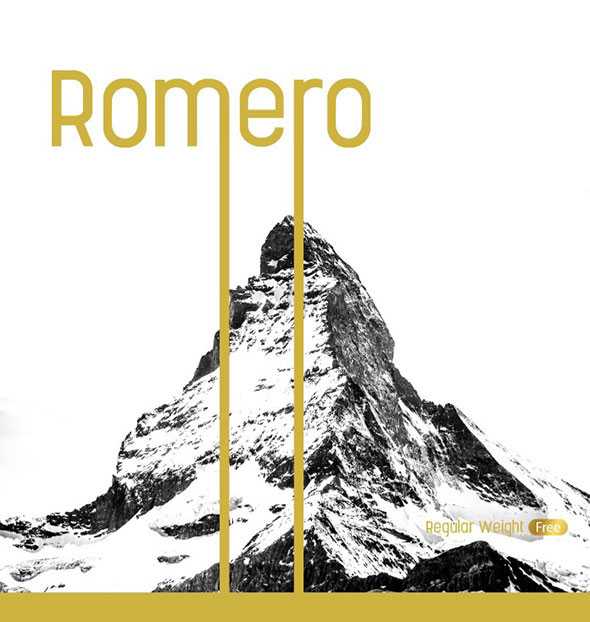
Ozymandias
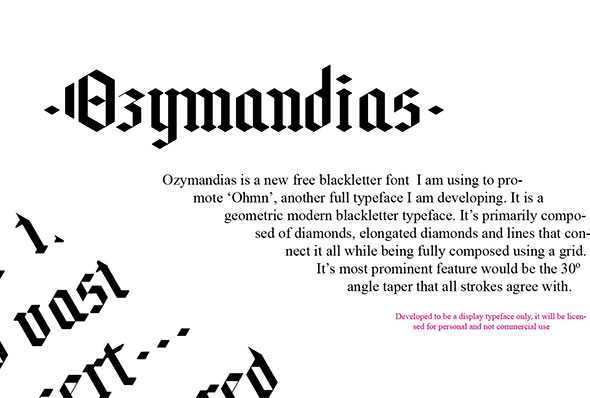
Ponds
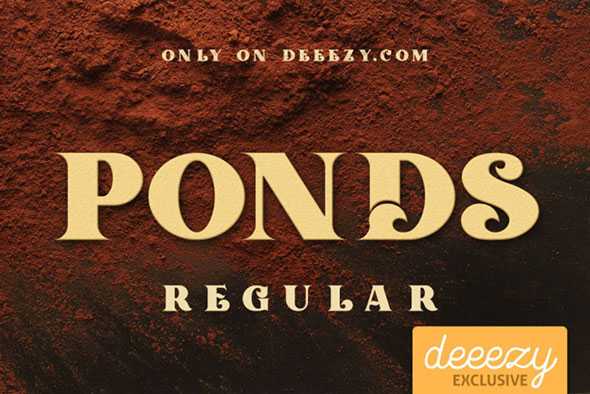
High Life
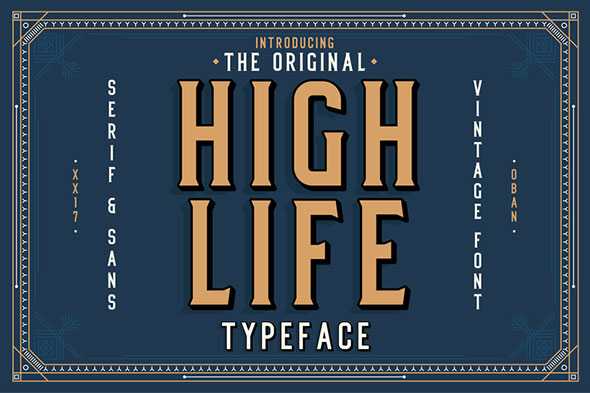
David Carson
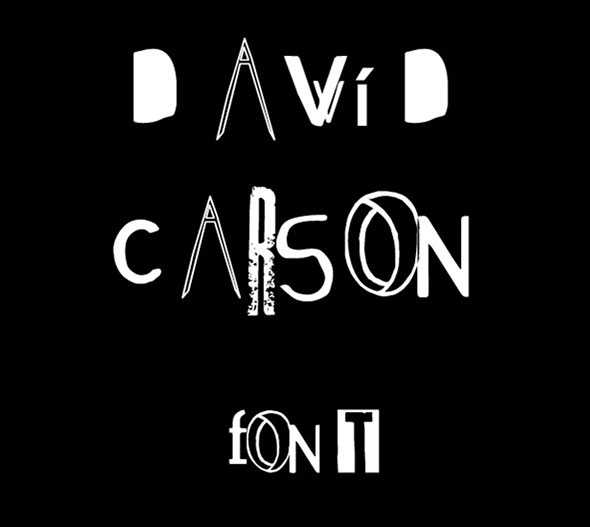
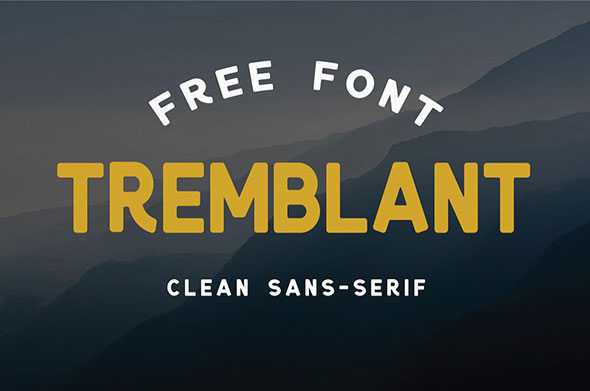
HOT ROD
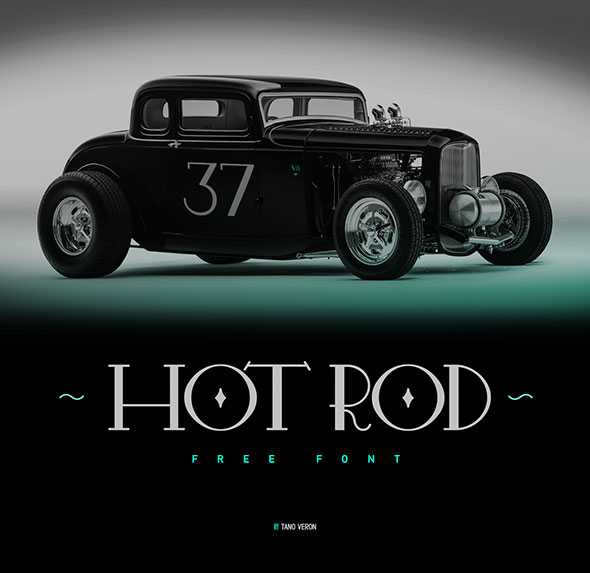
Freeday Script & Sans Font
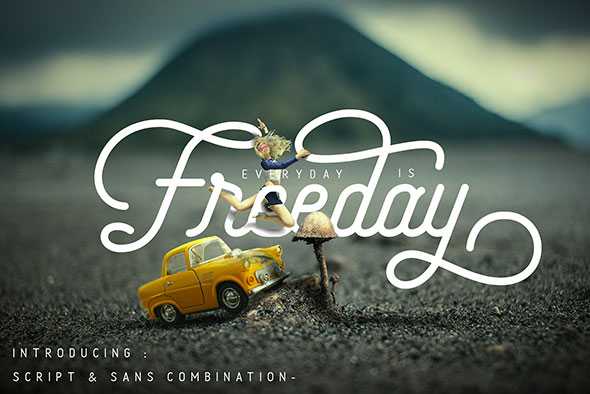
Bahagia
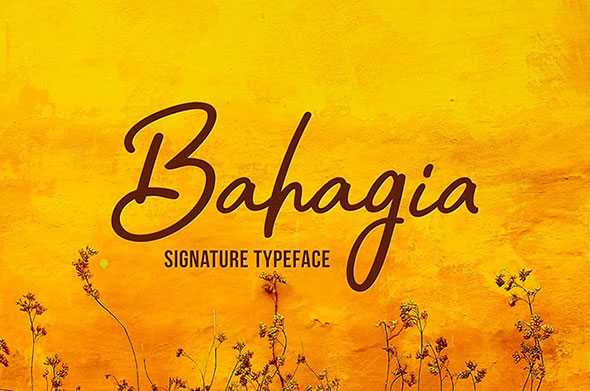
Bant Achillers
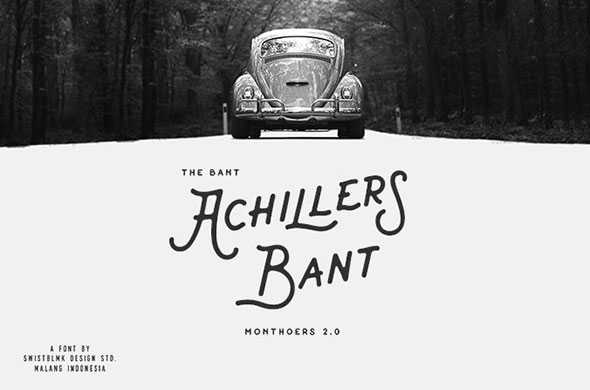
Старый стиль
Старый стиль шрифтов основан на технике письма клинописью. Это видно по характерным засечкам строчных букв, которые всегда располагаются под углом, а все изогнутые линии буквенных форм имеют переход от толстого штриха к тонкому. Можно провести небольшой эксперимент – если провести линию через тонкие части закругленного штриха, то она всегда будет диагональной.
Такие шрифты считаются наилучшим вариантом для набора длинного текста. Во-первых, у них очень мало отличительных особенностей, мешающих чтению, а во-вторых, глаз как бы цепляется за засечки, что облегчает сам процесс чтения.
Современный стиль
Современный стиль или так называемый Modern, а так же Didone. Внешний вид современного стиля отличается некой отчужденностью шрифтов. Здесь уже нет такого, явного, подражания клинописи. У шрифтов современного стиля засечки горизонтальные и более тонкие, а так же явно выраженный, контрастный переход от толстой линии к тонкой и очевидный вертикальный нажим.
Шрифты современного стиля очень хорошо смотрятся при написании крупным кеглем. Однако, из-за резкого перехода от толстой линии к тонкой, они не удобны для длительного чтения. Поэтому лучше всего их использовать для заголовков и логотипов.
Египетский стиль
Египетский стиль иногда называется Claderon, по названию первого шрифта этой группы. Их отличительная особенность – едва заметный переход от более толстой линии к тонкой, а зачастую и вообще его отсутствие. Засечки строчных букв у этих шрифтов горизонтальные и толстые. Еще одно название этой группы Slab Serif, что в переводе с латинского означает – прямоугольные.
4. Декоративный шрифт
К декоративным относятся большинство шрифтов, не попадающих под остальные параметры. Это очень большая и разнообразная категория шрифтов, и их количество увеличивается день ото дня. Из-за своей экстравагантности, их стоит применять очень дозировано и аккуратно. Это могут быть логотипы, заголовки или отдельные надписи.